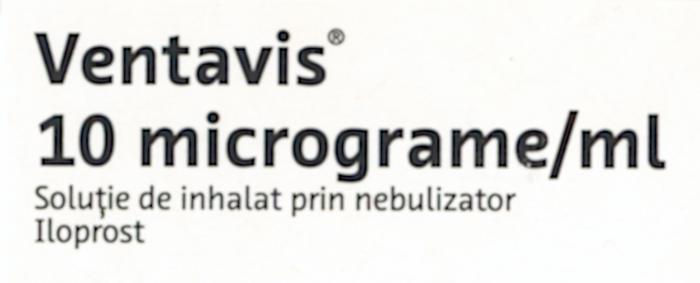
Was ist das für eine Schrift
Ich bin schon lange auf der Suche nach dieser Schrift,
kann diese aber leider nicht finden.
Vielleicht kann mir ja jemand helfen?
Das ist die "Schering", ursprünglich von Alessio Leonardi für den Schering-Konzern (Jetzt: Bayer) gezeichnet. Gibt es in Sans, Serif und Letter, war aber ein Kundenauftrag und daher nicht käuflich zu erwerben.